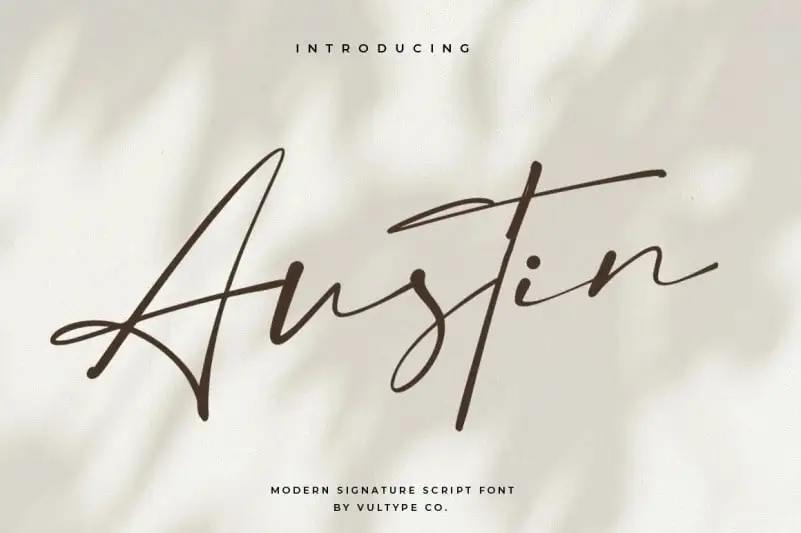
Austin Handwritten Font – Download Grátis
A Austin Handwritten Font é uma elegante tipografia script que traz a essência do estilo artesanal à sua obra de arte digital. Desenvolvida por Vultype, esta fonte tem um tom natural e orgânico, caracterizada por ligaturas e swashes que adicionam um toque realista de escrita com as mãos aos seus trabalhos. Austin é perfeito para projetos pessoais ou profissionais, oferecendo uma aparência fluida e autêntica que cativa sua atenção pela sua estética distintiva e eterna. Descubra por que esta fonte é tão amada pelo seu estilo único, ideal tanto para a criação de logos quanto para a designação de websites ou editoriais, trazendo um toque natural e moderno à sua arte digital.